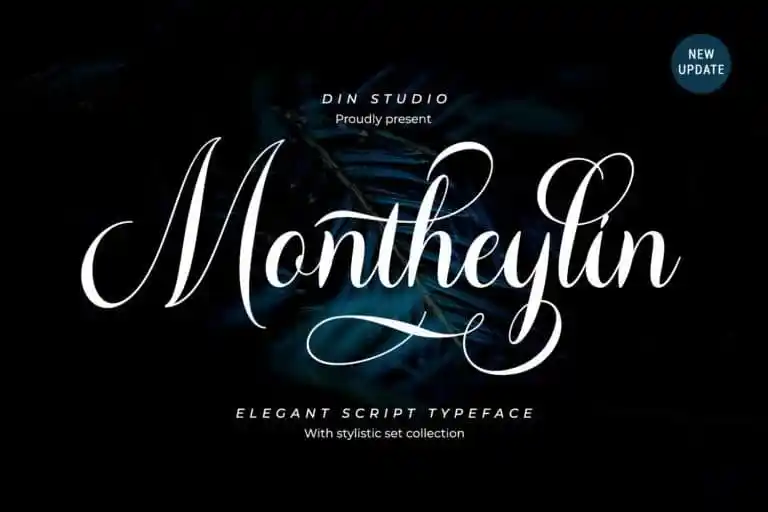
Montheylin Calligraphy Font – Download Grátis
A Montheylin Calligraphy Font é uma escolha perfeita para quem busca uma tipografia que traz a essência do estilo calligrafico moderno e versátil, combinando elegância com uma pitada de leveza e criatividade. Este font é especialmente indicado para projetos profissionais como branding ou logomarcas, mas também se destaca em áreas mais criativas, como criação de identidades gráficas para casamentos e citações. Com um design intuitivo que torna sua utilização simples e prazerosa, a Montheylin Calligraphy Font traz uma abordagem lúdica que permite a seus usuários explorar e combinar diferentes traços, criando texturas e estilos únicos. Seja para marcar uma celebração especial ou para ilustrar um texto com estilo, esta font é certamente o melhor aliado para quem busca adicionar a sua peça de trabalho gráfica uma personalidade moderna e inspiradora.